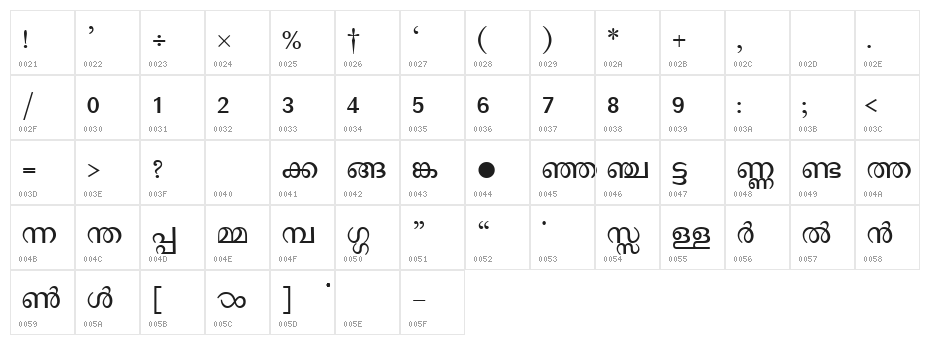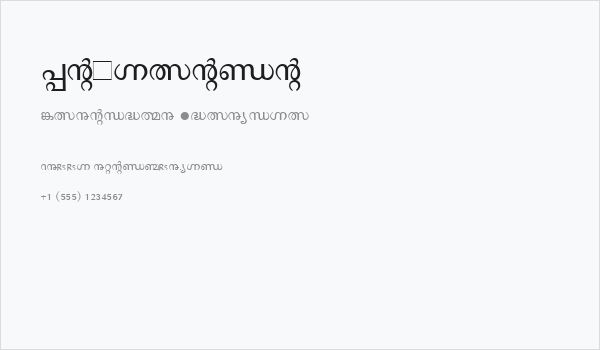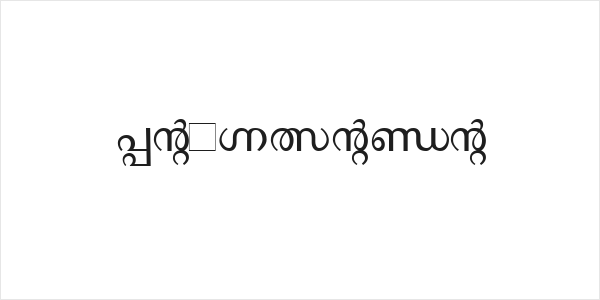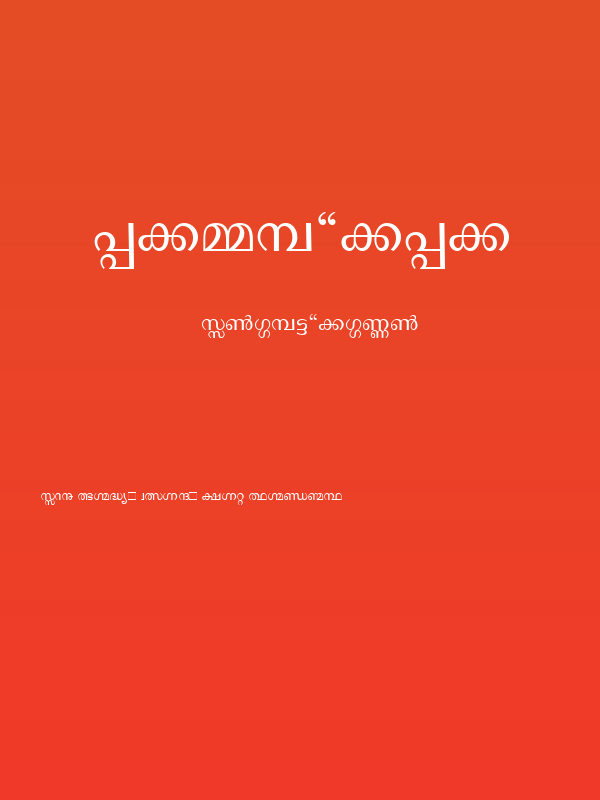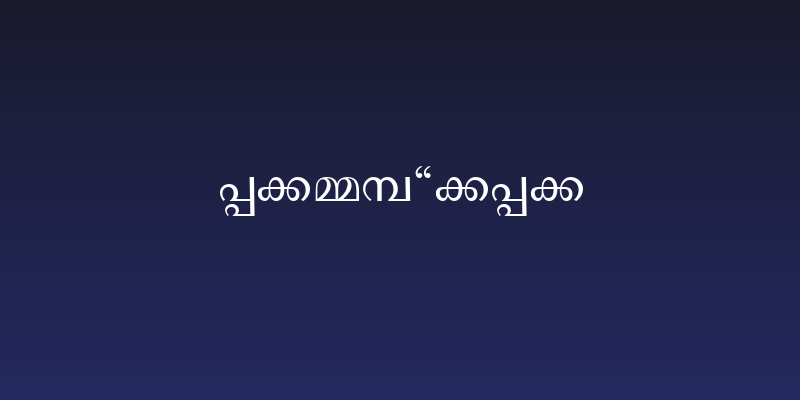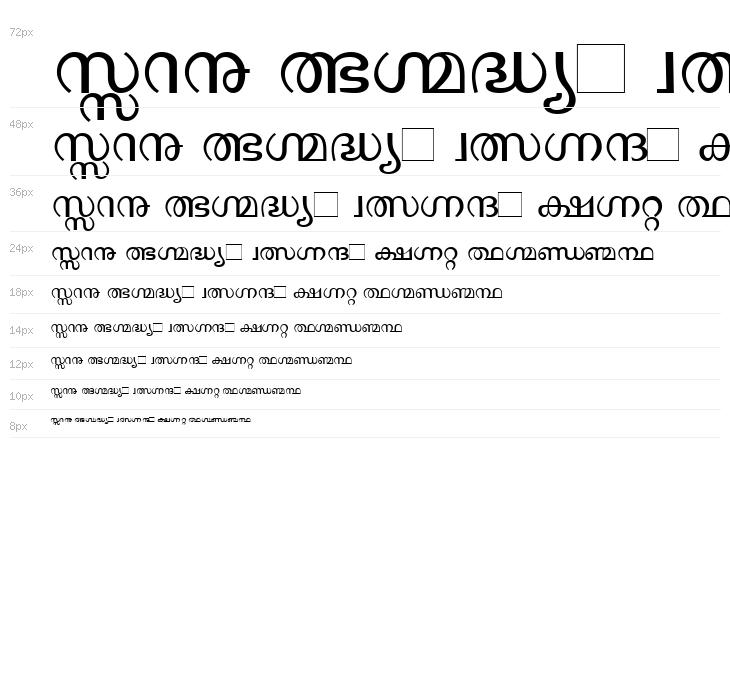
Manorama Font
✎ Round
| Kategorien | Round |
| Anwendungsfall | Headlines, Body text, Logos |
| Vorgeschlagene Projekte | Ideal for use in digital interfaces, print media, branding, and signage due to its clarity and modern aesthetic. |